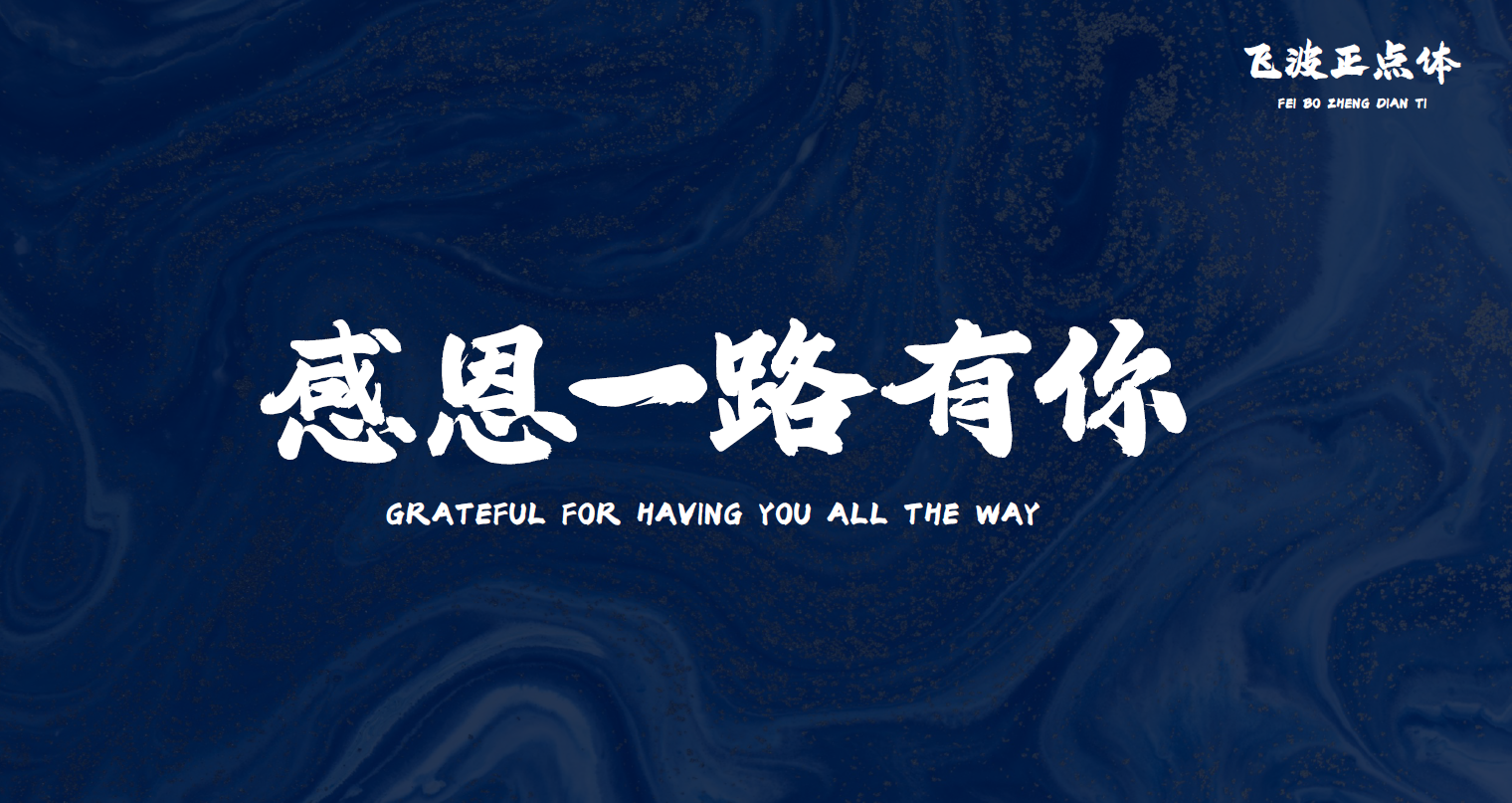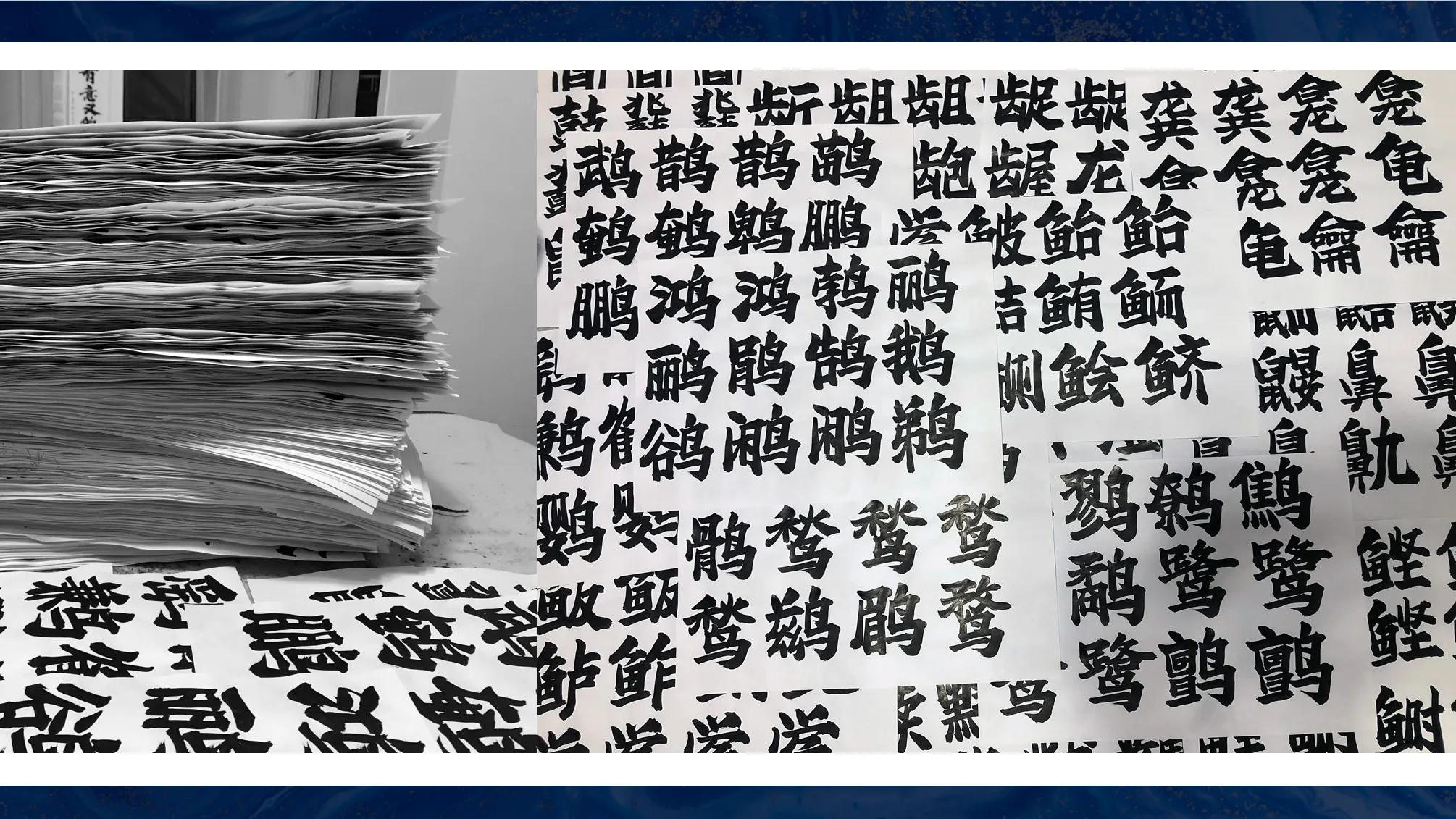
免费商用毛笔字体下载飞波正点体,这款字体结构工整、笔画清晰,兼顾美观与易读性,适用于标题、正文、海报、包装、LOGO 等多种场景。字形优雅稳定,风格百搭耐看,适配日常排版与创意设计,让文字呈现更舒适、更具质感。免费商用毛笔字体下载飞波正点体一笔一画,皆是细节,以均衡的比例、流畅的线条打造舒适视觉体验,字形端正大气,风格简约现代。无论是商业设计、品牌宣传还是日常排版,都能轻松驾驭,让文字更有格调与力量。免费商用毛笔字体下载飞波正点体字体下载。
字体创作介绍
飞波正点体由本人从毛笔手写到后期软件封装,创作历时一年时间,完成共7千多字。初次制作字库,经验不足之处,欢迎指正。
字体风格稳重,气势上扬,笔画厚重有力是此套字库的特点。适用于各种标题大字排版,电影海报、包装、电商、品牌名称、漫画、影视综艺、游戏、各类商业海报、户外广告标题等。
• 优化和新增英文字母标点符号若干个。
• 优化竖版排版下的标点符号位置显示问题
• 修正错别字“倒”字